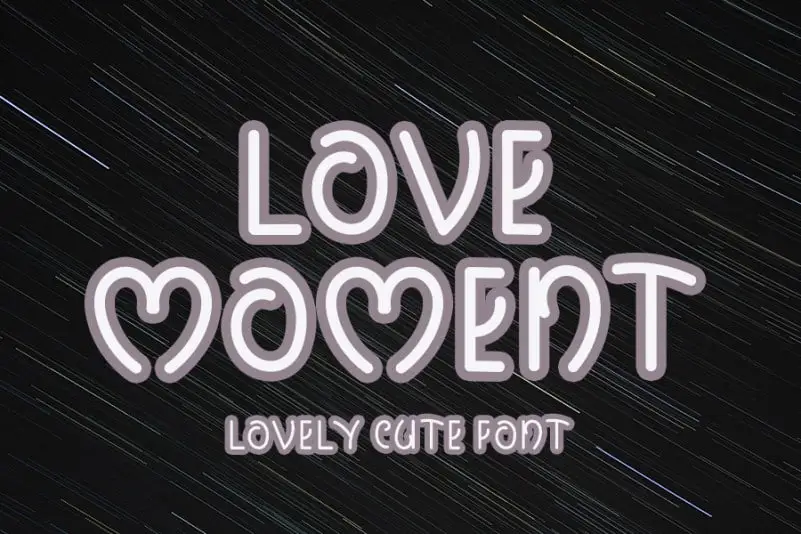
Love Moment Display Font – Download Grátis
A Love Moment Display Font é uma excelente escolha para quem busca criar designs únicos e modernos que expressam amor com classe. Inspirada nas influências manuscritas, essa fonte mantém seu estilo sofisticado ao mesmo tempo que se atualiza e evolui de forma fresca e inovadora. Seus recursos versáteis a tornam perfeita para uma variedade vasta de ideias criativas, desde as assinaturas até os títulos em cartões de papelaria personalizados. Ideal tanto para aqueles que valorizam um estilo tradicional quanto para aquelas pessoas buscando algo mais moderno e interessante. A Love Moment Display Font é a escolha perfeita para quem busca uma fonte elegante e versátil para expressar seu amor de maneira única e contagiante.